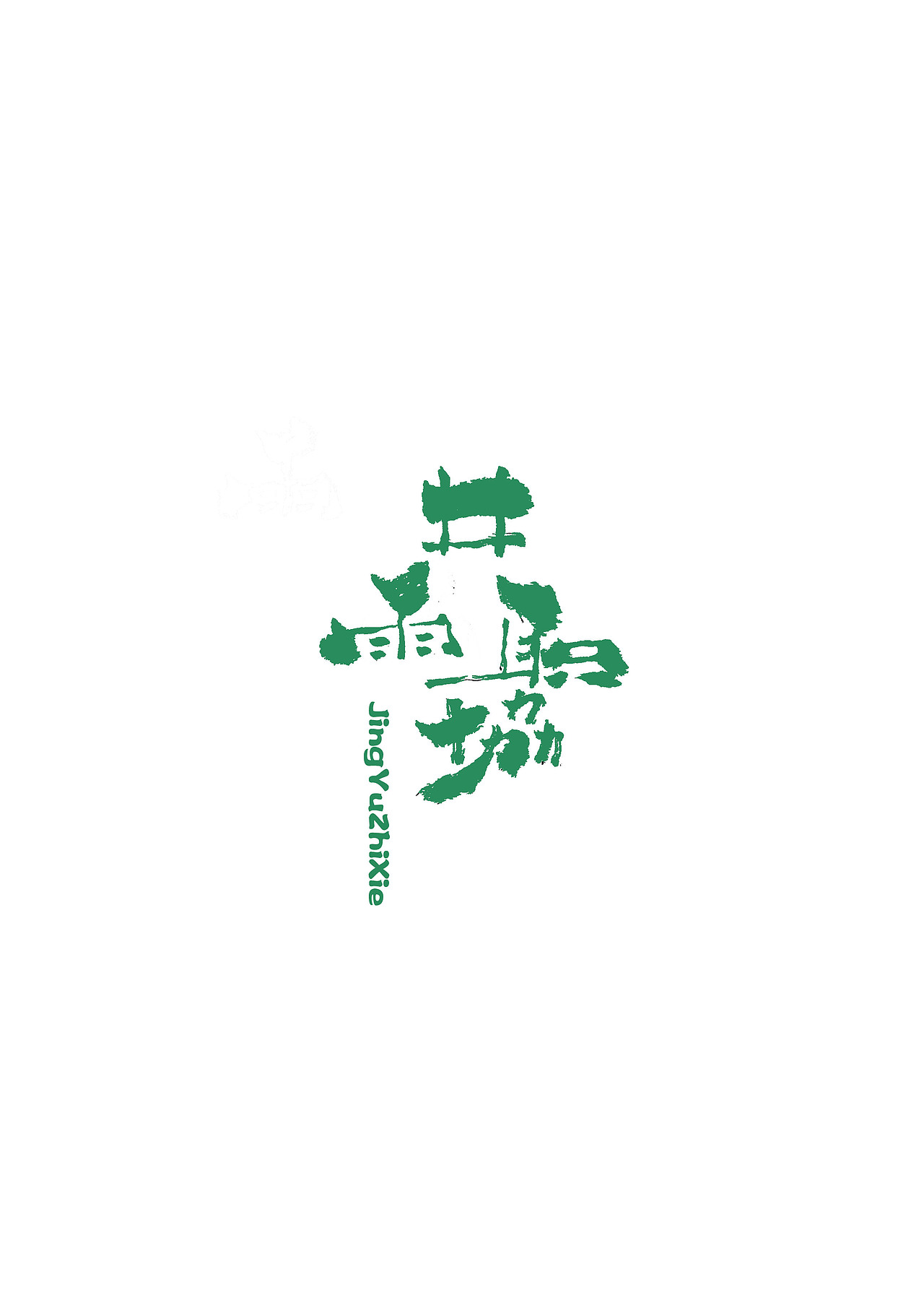
《井雨职协》单位定制手书字体
需求方的要求就是:没有要求!!!🤔🤔🤔
传说中的要求就是好看就行
于是乎想想名字叫井雨,并且原logo 的标准色是清新绿;所以呢就想要做成活泼灵动些的感觉,不能死板笔直
试了多次以后,得出了下面这款毛笔手写的格调作品; 刻意的运用了些枯笔飞白的效果,绿中又白,更显清新。
个别笔画尤其是起笔的位置,进行了加重的处理,顿笔效果突出,与其他笔画的纤细形成明显的对比,整体显得灵动些。